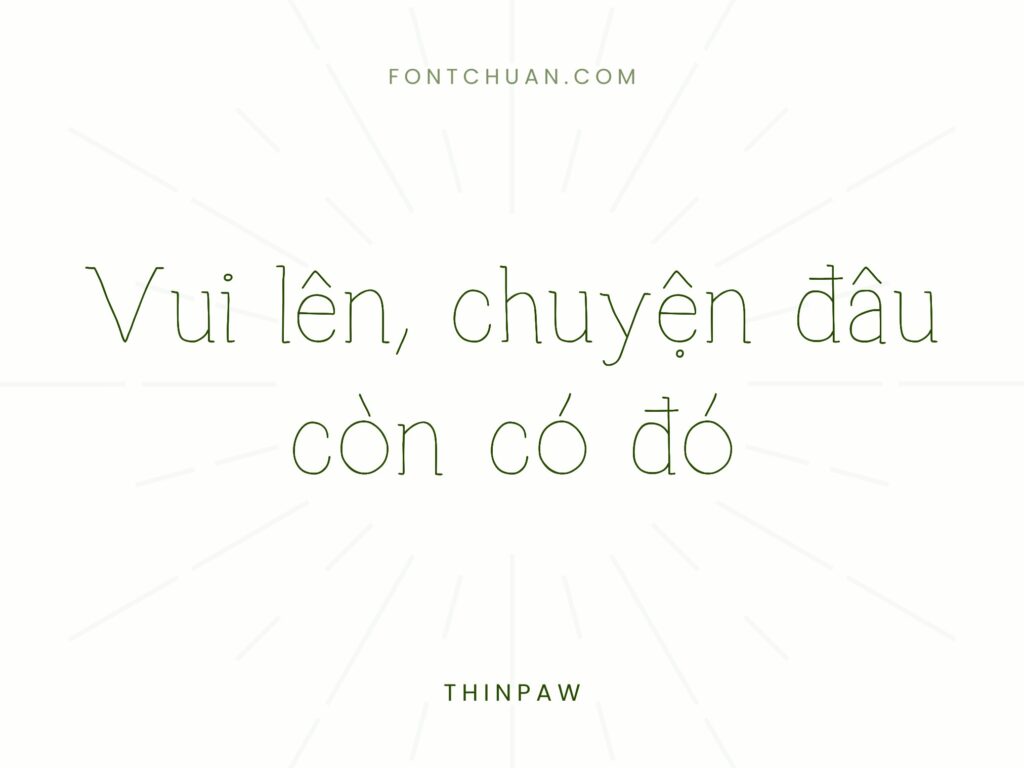
Font iCiel Thinpaw Việt Hóa
Tác giả Font: Vaclav Krejci
Việt hóa bởi: Iciel
Thinpaw là một kiểu chữ sans-serif hiện đại, được thiết kế với các đường nét mảnh mai và tinh tế, tạo cảm giác thanh lịch và tối giản. Font này phù hợp cho các thiết kế như tiêu đề, logo, poster và các ấn phẩm truyền thông cần sự rõ ràng và hiện đại. Đặc biệt, Thinpaw đã được Việt hóa bởi iCiel, hỗ trợ tiếng Việt cùng nhiều ngôn ngữ khác, đáp ứng nhu cầu đa dạng của người dùng. Bạn có thể tìm thấy font này trong bộ sưu tập font của iCiel trên các trang web như ROMhub.io.
Về đặc điểm thiết kế, Thinpaw sở hữu các ký tự gọn gàng, cân đối với độ tương phản thấp, mang lại cảm giác dễ chịu cho mắt. Font này còn thích hợp cho các ngành nghề như quảng cáo, công nghệ, giáo dục và bất động sản, cùng các sự kiện đặc biệt như lễ hội, sinh nhật, Halloween và Trung thu.